Бродвей
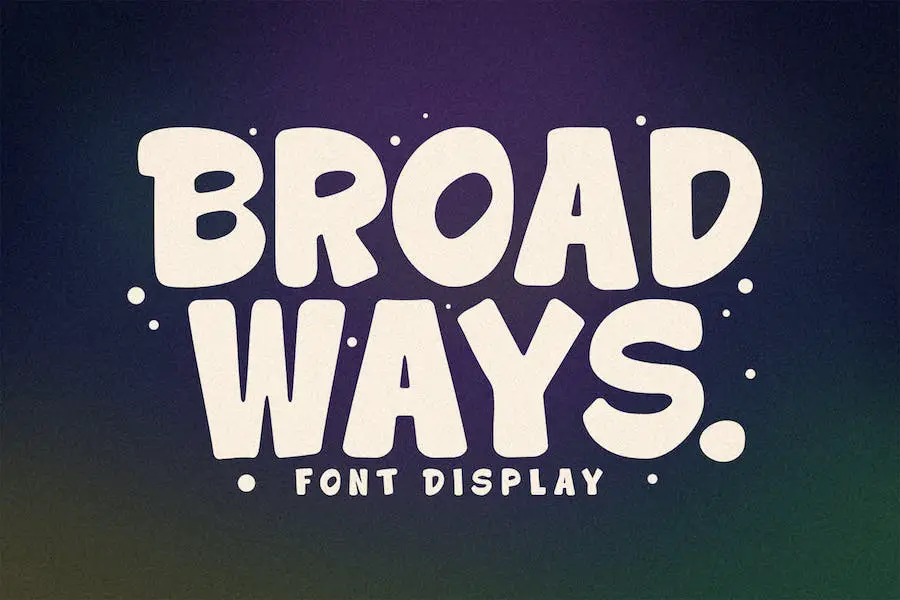
Broadways — универсальный шрифт, который может улучшить дизайн различных проектов. Благодаря использованию заглавных букв, цифр, базовой пунктуации и многоязычной поддержке он идеально подходит для брендинга, поделок, приглашений и многого другого.
Этот шрифт — отличный инструмент для графических дизайнеров, желающих улучшить свои проекты. Широкий спектр символов и символов обеспечивает творческую гибкость, что делает его подходящим для любой концепции дизайна. Кроме того, его многоязычная совместимость гарантирует, что он может обслуживать разнообразную аудиторию.
Работаете ли вы над логотипом, плакатом или даже персонализированными канцелярскими товарами, Broadways поможет вам. Его стильный и привлекательный внешний вид придаст любому проекту нотку элегантности, выделяя его из толпы.
С Broadways вам больше не придется беспокоиться о поиске идеального шрифта для ваших творческих начинаний. Его универсальность и обширный набор символов делают его надежным выбором для различных дизайнерских задач. Так зачем соглашаться на меньшее, если вы можете улучшить свои проекты с помощью этого удивительного шрифта?
Бродвей
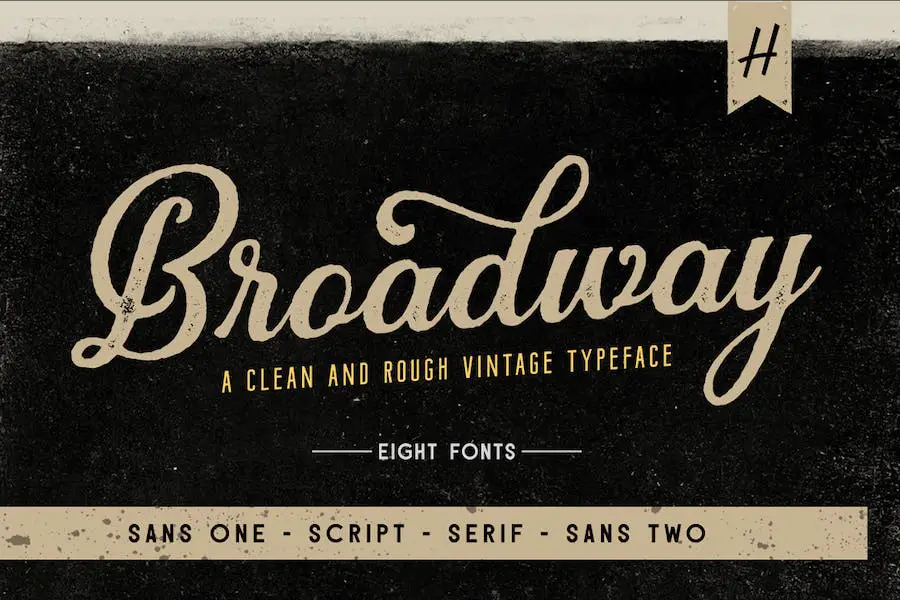
Broadway — это шрифт, вдохновленный винтажным шрифтом, придающий ему нотку ностальгии и в то же время современный.
Благодаря как обычным, так и сокращенным вариантам шрифта без засечек, Broadway предоставляет дизайнерам гибкость в создании идеальной типографики для своих проектов.
Обычный стиль Бродвея имеет классический вид, напоминающий старые бродвейские плакаты и афишы. Его элегантные изгибы и чистые линии делают его подходящим для широкого спектра проектов графического дизайна, добавляя изысканности любому макету.
Создаете ли вы приглашение в винтажном стиле или стильный логотип, обычный стиль Бродвея — универсальный выбор.
Для тех, кому нужен более компактный и компактный шрифт, Broadway также предлагает сокращенный вариант. Этот стиль отличается более узкими буквами, что позволяет разместить больше текста на меньшем пространстве без ущерба для читаемости.
Он идеально подходит для создания привлекающих внимание заголовков или придания смелости вашему дизайну.
Бродвей
Broadway — это винтажный монолинный шрифт, вдохновленный старым бродвейским стилем, придающий вашим проектам стильный и ретро-стиль. Благодаря своей вневременной привлекательности этот шрифт идеально подходит для графических дизайнеров, желающих придать своим проектам нотку ностальгии.
Этот шрифт имеет монострочный стиль, что означает, что каждый штрих имеет одинаковую толщину. Это придаст вашему тексту единообразный, сбалансированный вид, который добавит ему ретро-шарма. Независимо от того, разрабатываете ли вы логотипы, плакаты или приглашения, Broadway привнесет в вашу работу нотку винтажной элегантности.
Одной из выдающихся особенностей Бродвея является его универсальность. Его можно использовать как для текста заголовка, так и для основного текста, гарантируя, что весь ваш дизайн будет целостным и визуально привлекательным.